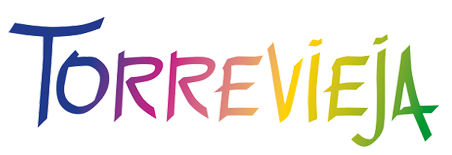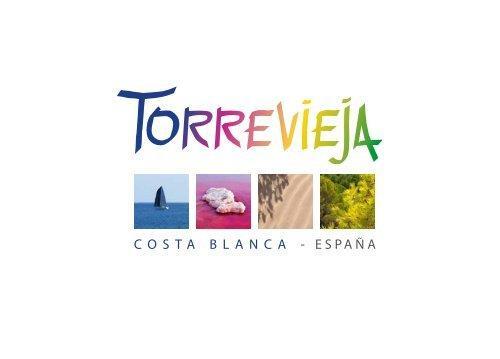
Schrift vom Logo für T-Shirt (Torrevieja)
Ich würde gern ein T-Shirt designen mit der Schriftart dieser spanischen Stadt Torrevieja.  Diese Schrift verwendet das Tourist Office. Welche Schrift ist das bitte?
Hallo @Doris, das wird kein Font, sondern einfaches digitales Lettering sein. Mindestens das A und das T würden in einem Font für Probleme sorgen. Ja: Theoretisch könnten diese beiden Buchstaben zwar modifiziert worden sein. Doch sind die Buchstaben auf eine Art und Weise aufgeführt, die nicht auf die Sorgfalt schließen lassen, die eine digitale Schriftart erfordert.